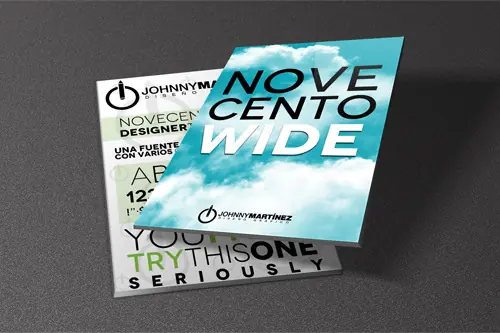
Novecento Wide | Fuente tipográfica para Diseñadores
Esta vez les presento "Novecento Wide". Una fuente muy bonita con una linda disponibilidad de grosores (Light, Book, Medium, DemiBold y Bold)
Es muy elegante, clara, perfecta para jugar con ella y crear textos atractivos.